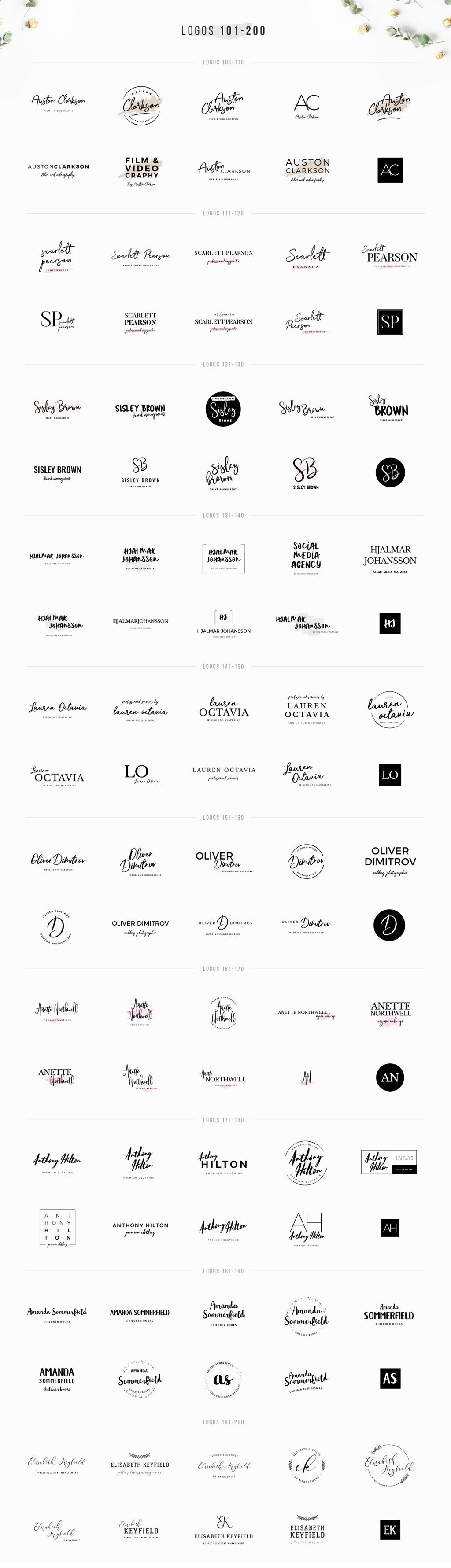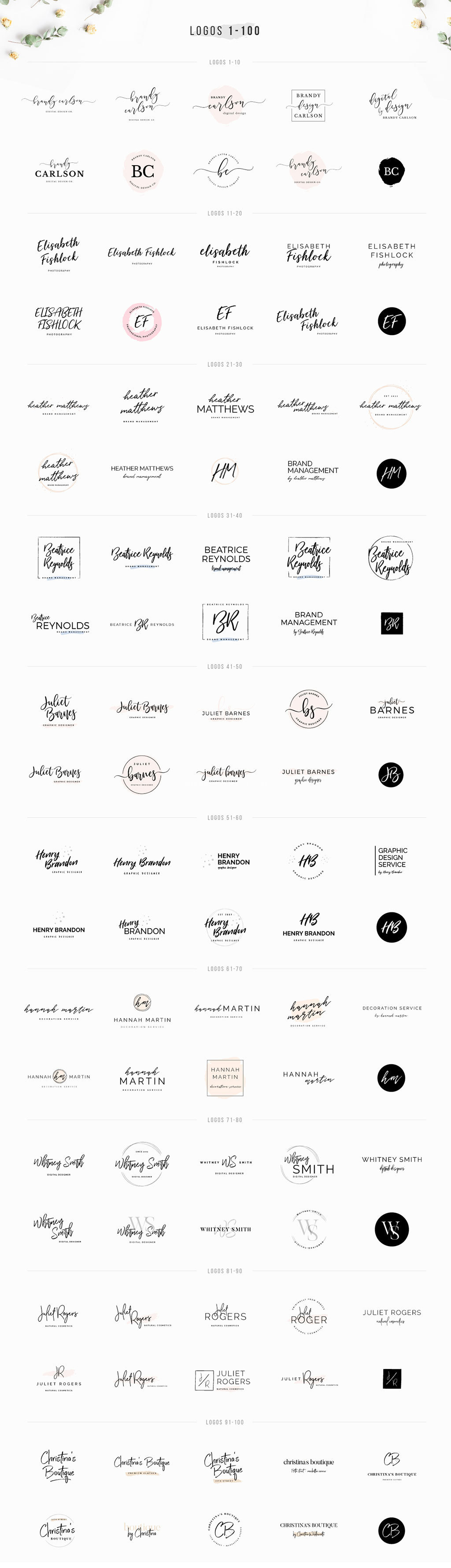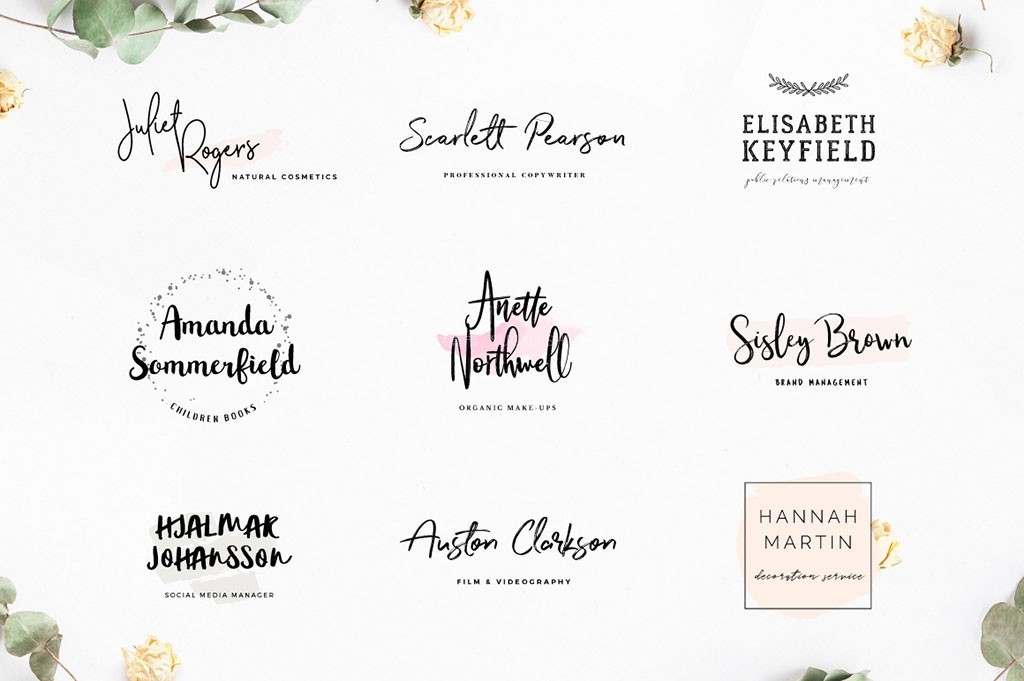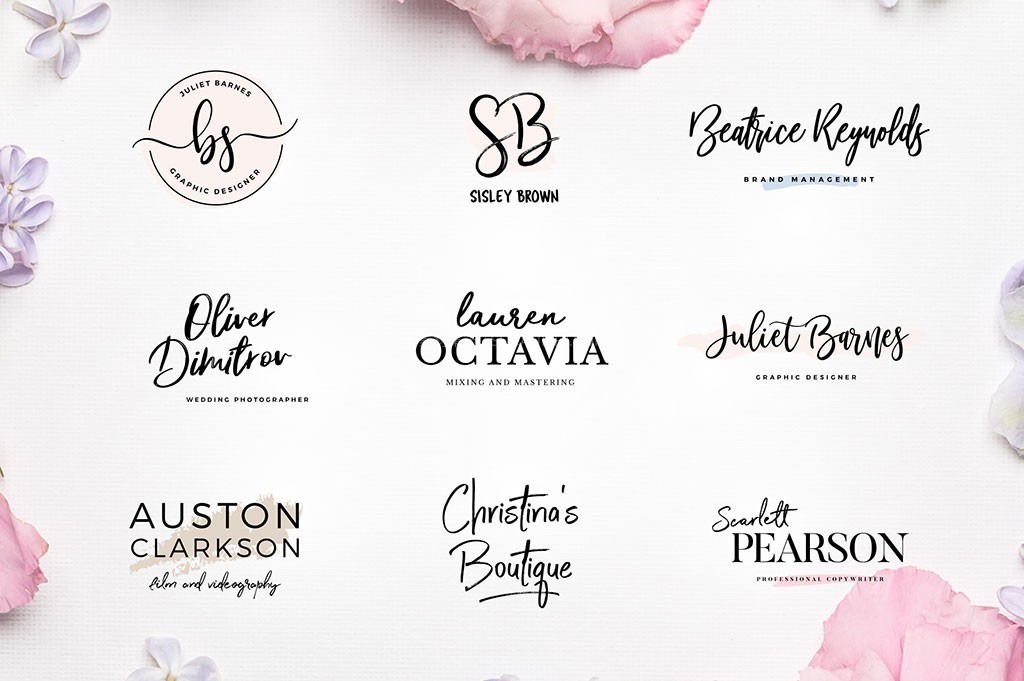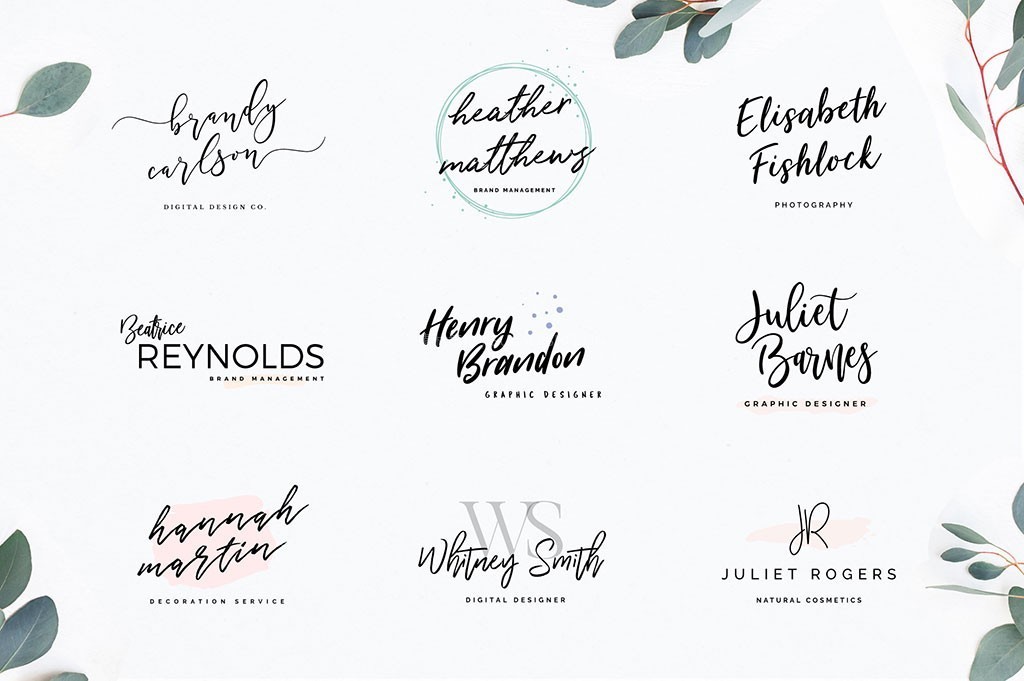
21款现代英文设计字体包(含53种字型)+ 200套可编辑Logo模板
精选21套高品质现代设计字体,涵盖53种丰富字型,并包含热销数千份的明星字体 Southfield 与 Masterblush。合集额外附赠200套支持Photoshop及Illustrator深度编辑的原创Logo矢量模板,并附带免费外部搭配字体指引,满足自由设计师与创意团队从品牌标识、包装到现代排版的全部商用需求。
适用场景: 品牌Logo设计、包装视觉、海报排版、概念视觉、自由职业接单、现代平面设计、数字艺术创作